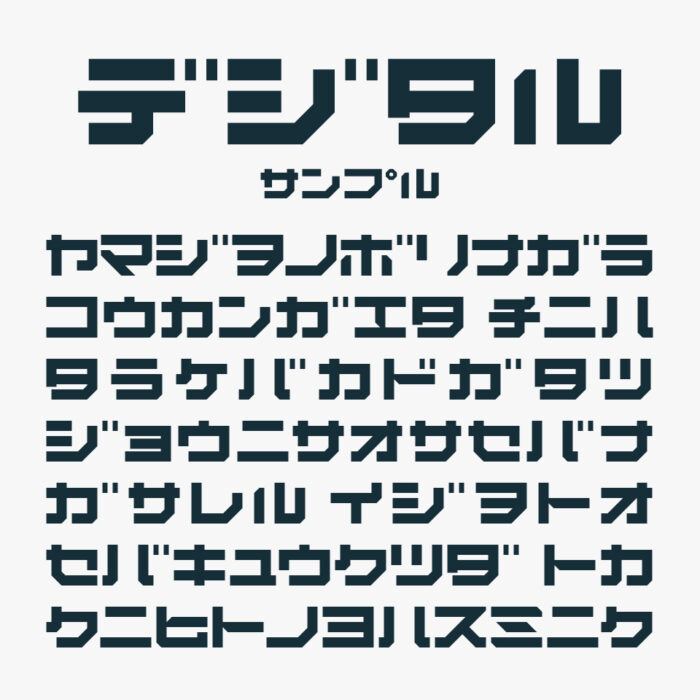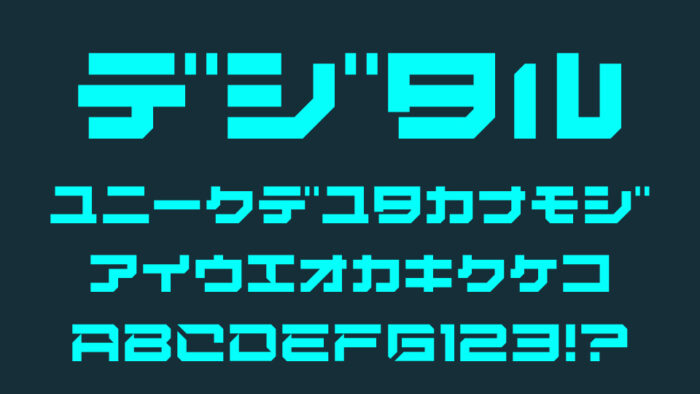
デジタルデゾレーションプラスフォントは、電子機器やデジタル表示を連想させる角張った極太なデザインが特徴のデジタルフォントです。
直線を基調としつつ、ディスプレイのドットを思わせるような構造の文字がデジタル的な未来な雰囲気を感じるデザインです。
無機質でありながらも独特の存在感があり、サイバーやテクノロジーをテーマにハマるフォントです。
収録文字は、カタカナ・アルファベット・数字・記号が収録されています。